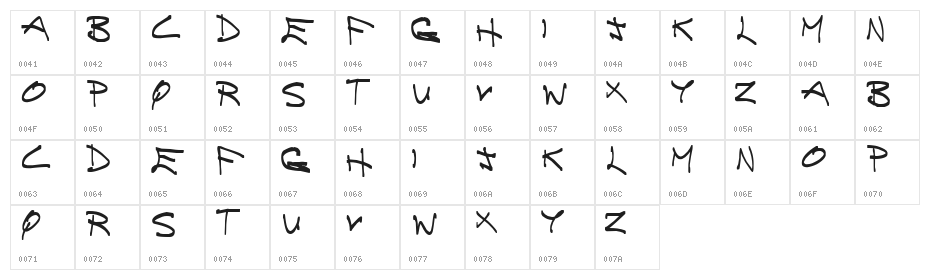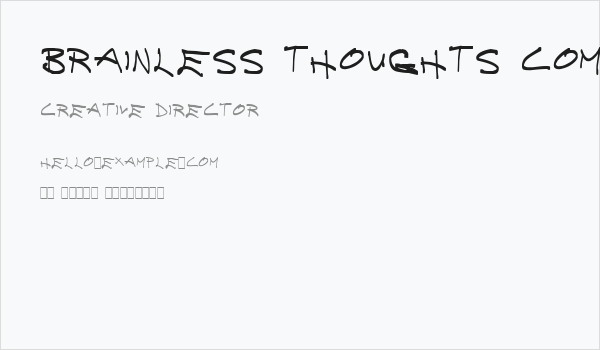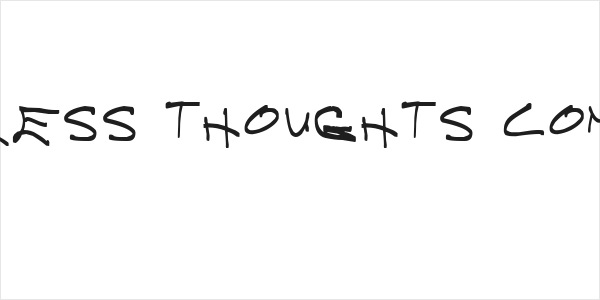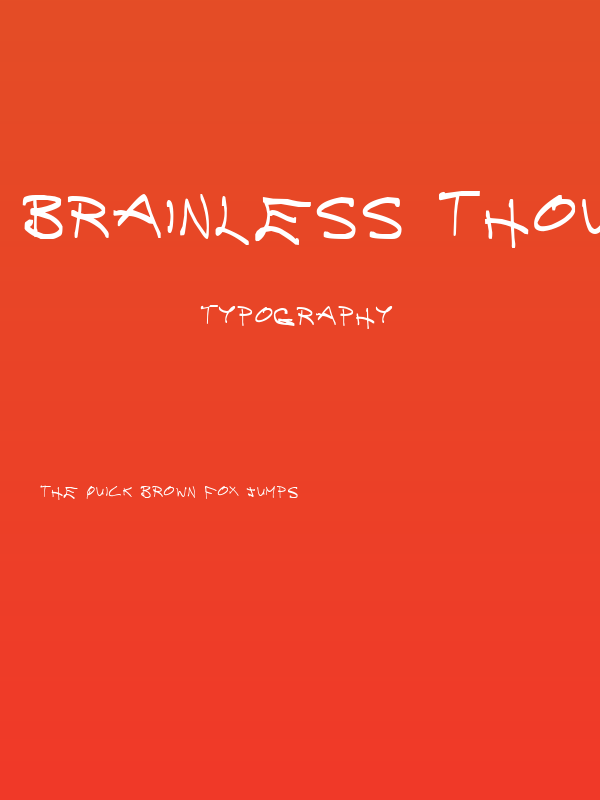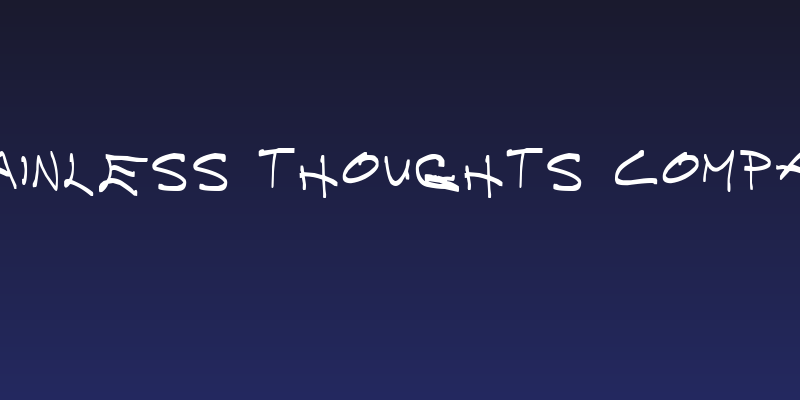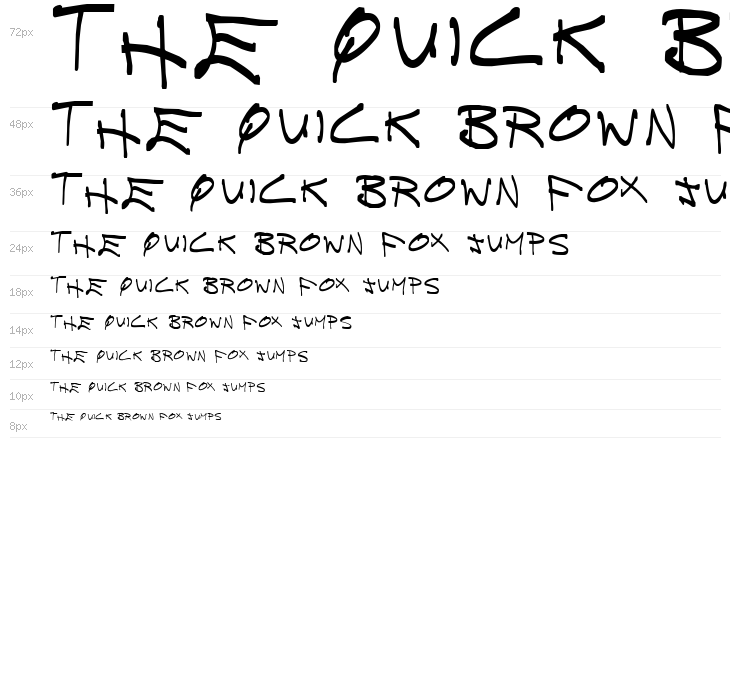
Brainless Thoughts Compact Font
✎ Handwritten
| 使用场景 | Logos, Headlines, Posters |
| 推荐项目 | Ideal for creative projects such as posters, album covers, or artistic branding that require a unique and informal touch. |